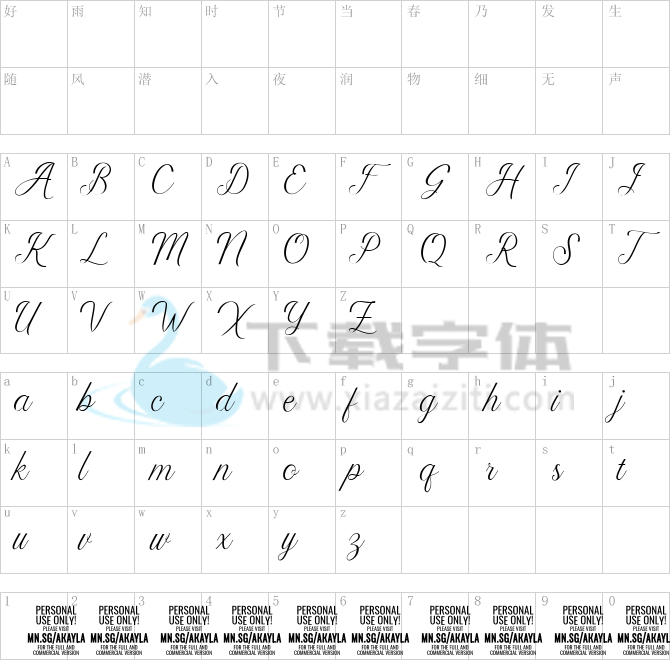
Akayla Script PERSONAL USE.ttf字体下载,这款字体结构工整、笔画清晰,兼顾美观与易读性,适用于标题、正文、海报、包装、LOGO 等多种场景。字形优雅稳定,风格百搭耐看,适配日常排版与创意设计,让文字呈现更舒适、更具质感。Akayla Script PERSONAL USE.ttf字体下载一笔一画,皆是细节,以均衡的比例、流畅的线条打造舒适视觉体验,字形端正大气,风格简约现代。无论是商业设计、品牌宣传还是日常排版,都能轻松驾驭,让文字更有格调与力量。Akayla Script PERSONAL USE.ttf字体下载字体下载。